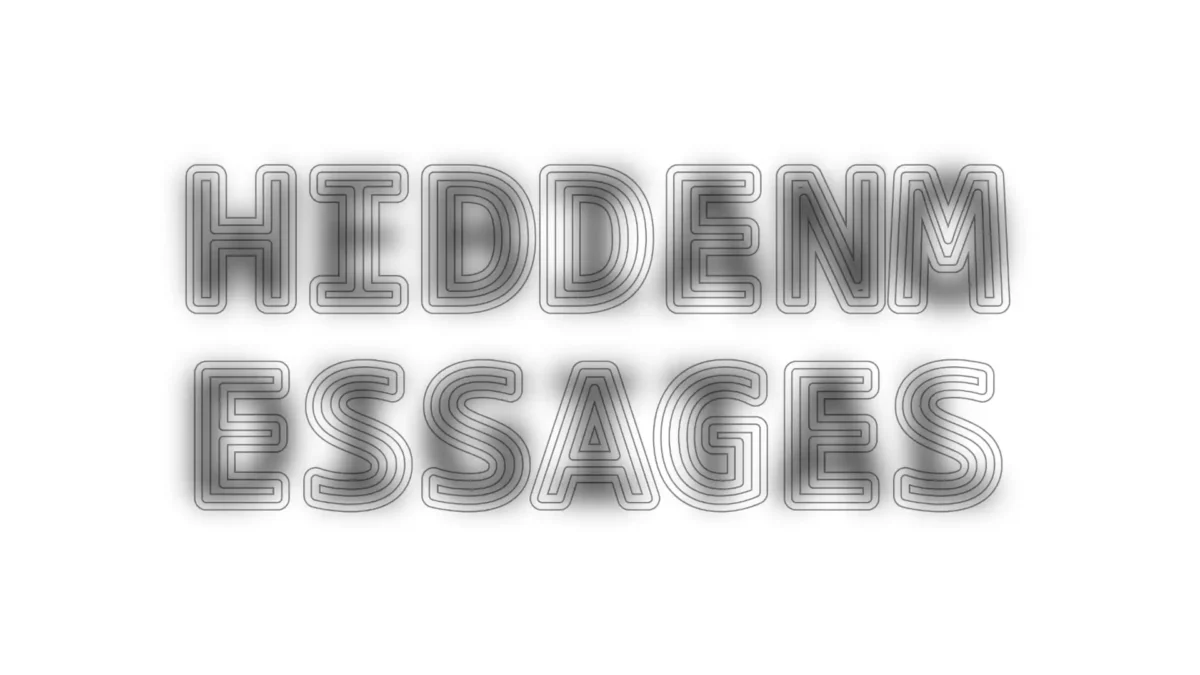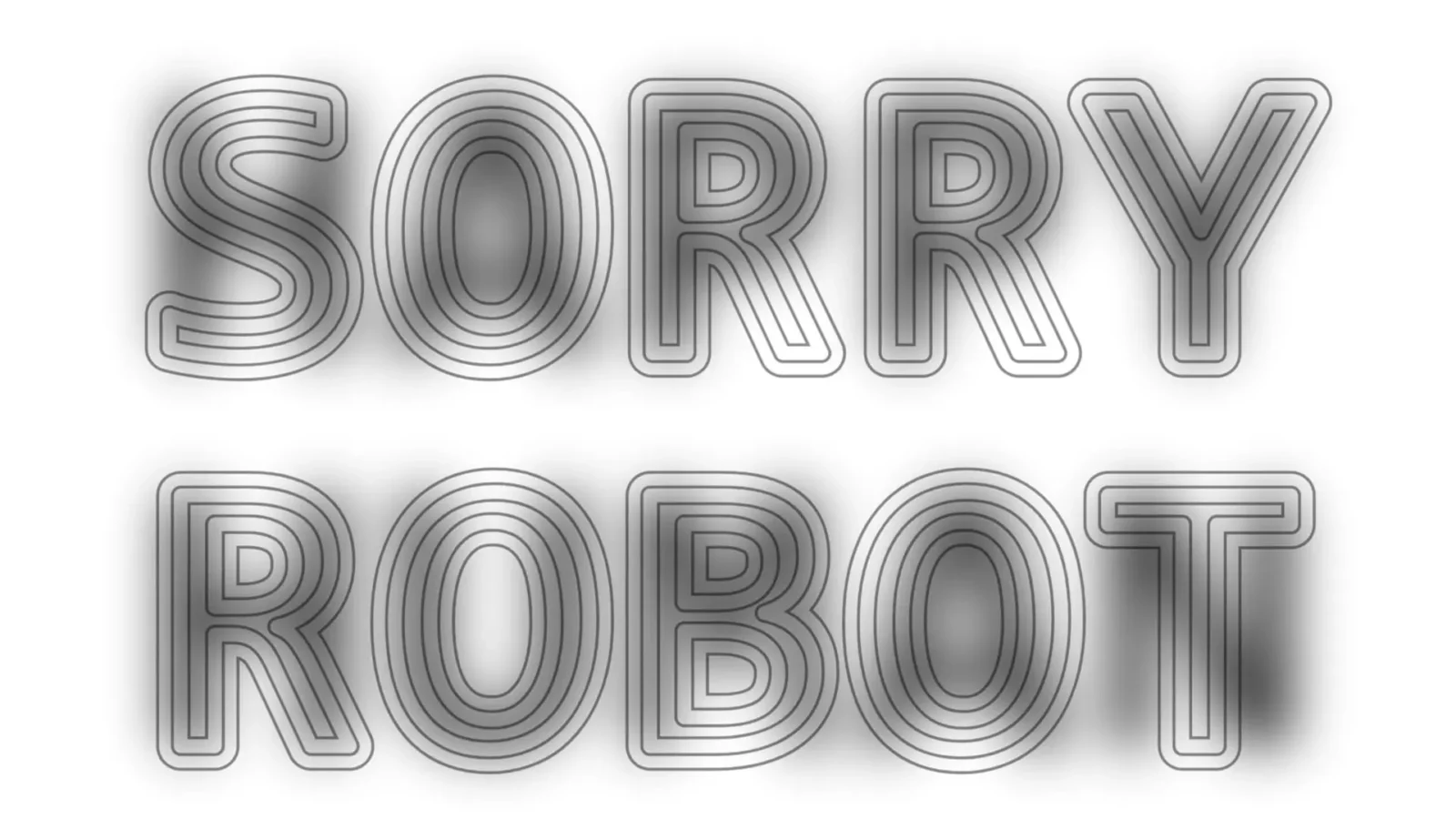
فونت ضد هوش مصنوعی معرفی شد؛ انسان می‌خواند، ربات‌ها فریب می‌خورند
گروهی از طراحان و پژوهشگران علوم کامپیوتر فونت ضد هوش مصنوعی ساخته‌اند که برای انسان قابل خواندن است، اما ربات‌ها و سامانه‌های خودکار را دچار اشتباه می‌کند.
به‌ گزارش سرویس هوش مصنوعی تک‌ناک،  یکی از نمونه‌های جالب این فناوری Decoy Font نام دارد. این فونت از یک ترفند بصری استفاده می‌کند تا دو پیام متفاوت را در یک تصویر متنی قرار دهد. در نتیجه، انسان و مدل هوش مصنوعی ممکن است از یک نوشته، پیام‌های کاملا متفاوتی دریافت کنند.
با گسترش استفاده از هوش مصنوعی در موتورهای جست‌وجو، پیام‌رسان‌ها و ابزارهای تولید محتوا، نگرانی درباره جمع‌آوری و استفاده از نوشته‌های انسانی نیز افزایش یافته است، در هین راستا پژوهشگران به سراغ این راهکار متفاوت رفته‌اند.
فونت Decoy Font چگونه هوش مصنوعی را فریب می‌دهد؟
ایده اصلی Decoy Font بر پایه یک خطای دید شناخته‌شده شکل گرفته است. این فونت دو لایه متنی را روی یکدیگر قرار می‌دهد. یک پیام با خطوط واضح در بخش جلویی دیده می‌شود و پیام دوم به‌ صورت تیره‌تر و محو در پس‌زمینه قرار دارد.
برای مثال، در یکی از نمونه‌ها، هوش مصنوعی ممکن است عبارت «Day Dream» را تشخیص دهد، درحالی‌که انسان می‌تواند پیام «Pay Bills» را نیز در پشت آن مشاهده کند.